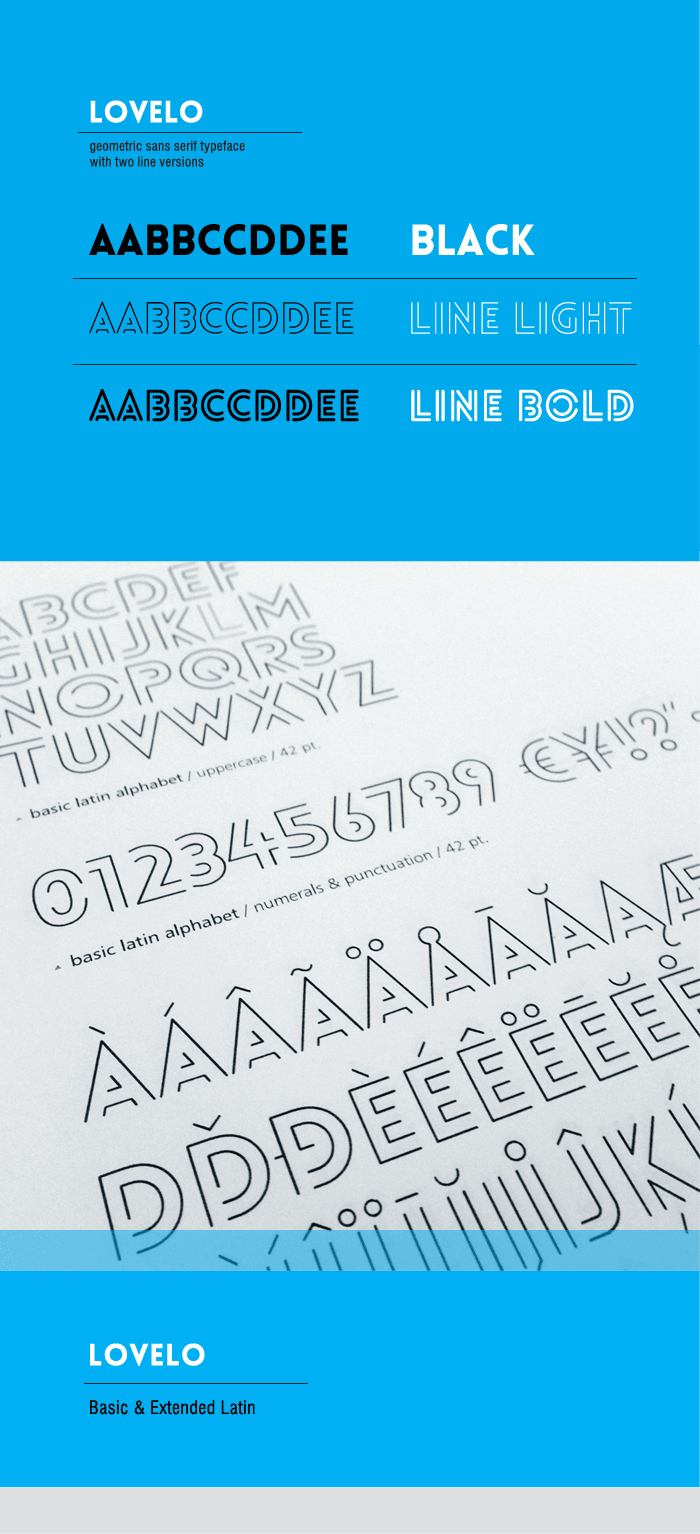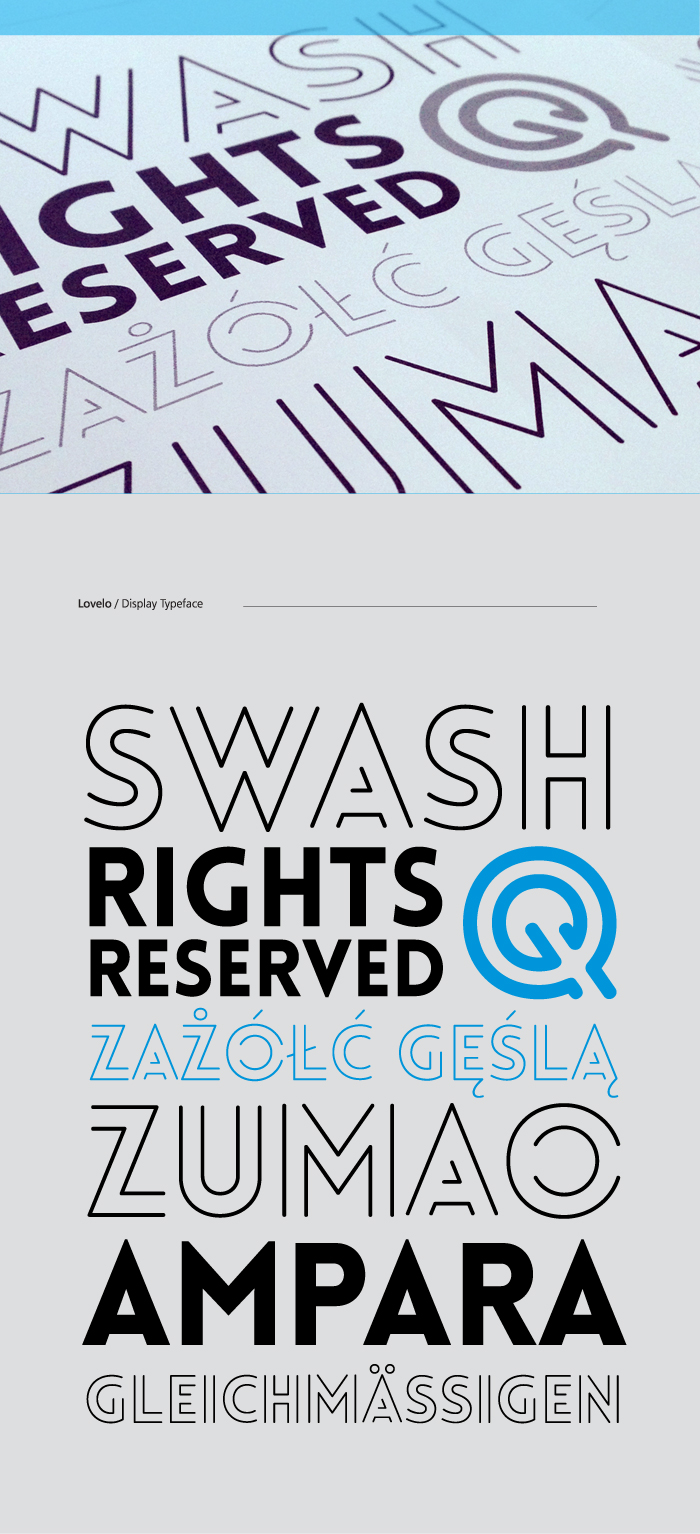
فونت Lovelo یکی از فونتهای زیبا و فانتزی انگلیسی بوده که توسط Fontfabric طراحی شده است . این فونت به سه شکل مختلف طراحی شده است . شما میتوانید در طرحهای خود از این فونت زیبا استفاده نمایید . امیدوارم این فونت مورد پسند شما قرار بگیرد .